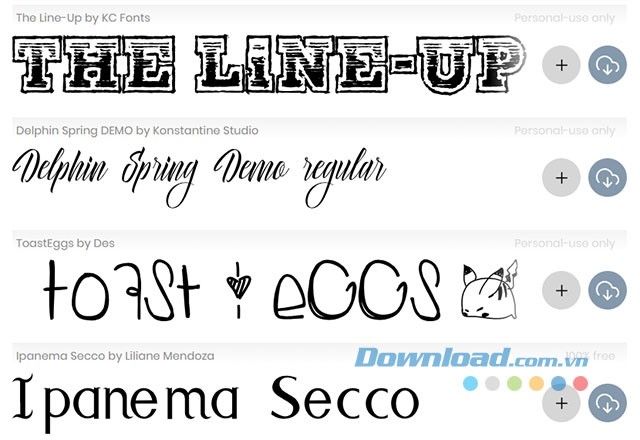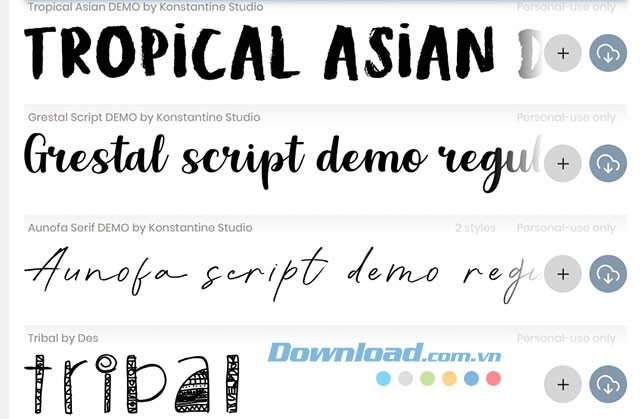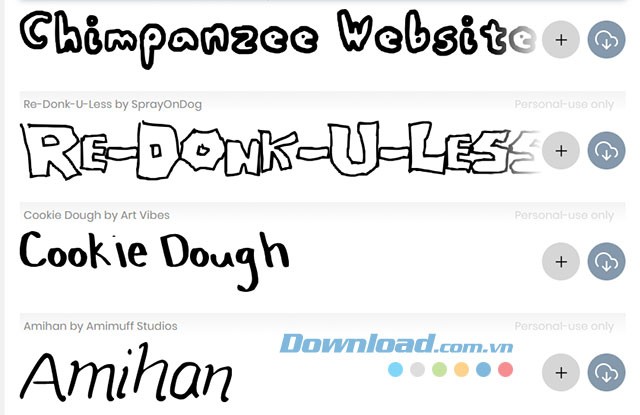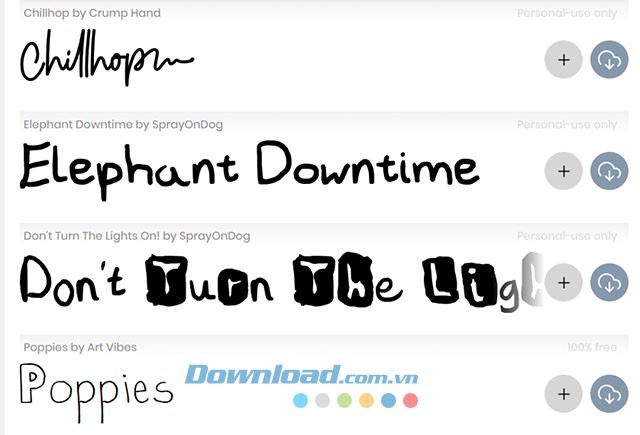
Font Chill: Bộ Font Chữ Đẹp Tiếng Anh Đầy Cảm Hứng
Font Chill là một bộ font chữ đẹp tiếng Anh, sở hữu rất nhiều kiểu chữ độc đáo và ấn tượng.
Bộ font chữ này hứa hẹn sẽ mang đến nguồn cảm hứng mới mẻ cho công việc, khơi gợi cảm giác tươi tắn, sảng khoái và niềm vui cho người sử dụng. Hãy tải và cài đặt ngay cho máy tính của bạn để bắt đầu quá trình sáng tạo những thiết kế thời thượng.
Chill – Xu Hướng Của Giới Trẻ
Sau thành công của ca khúc "Bài này Chill phết " do Đen Vâu và Min hợp tác, khái niệm "Chill" đã trở nên quen thuộc với giới trẻ Việt Nam.
Vậy, "Chill" thực sự có ý nghĩa là gì? Tại sao từ này lại được yêu thích đến vậy? Theo nghĩa đen tiếng Anh, "Chill" liên quan đến cảm giác lạnh lẽo, giá lạnh, hoặc ớn lạnh. Ví dụ, câu "There was a chill in the air" có nghĩa là "Không khí lạnh lẽo quá."
Tuy nhiên, cách mà giới trẻ Việt Nam sử dụng từ "Chill" lại mang một ý nghĩa hoàn toàn khác. Nó được hiểu như một từ lóng, tương đương với "Cool", "đẹp", "hay", "thú vị" hoặc "sảng khoái".
Nhìn chung, "Chill" mang ý nghĩa tích cực, do đó bộ Font Chill chắc chắn sẽ truyền cảm hứng sáng tạo đặc biệt, đặc biệt đối với giới trẻ.
Font Chill – Sự Lựa Chọn Mới Lạ
Bộ Font Chill là một tuyển tập gồm 21 font chữ đẹp, được thiết kế dành cho Word , mang phong cách "Chill" đặc trưng.
Đây không phải là những font chữ cứng nhắc như trong các bộ Font Vni , Bộ font TCVN3 hay Bộ font Unicode thông thường. Thay vào đó, bạn sẽ có những lựa chọn mới mẻ, mềm mại và độc đáo, chắc chắn sẽ làm hài lòng mọi người.
Bạn hoàn toàn có thể sử dụng Bộ Font Chill làm font chữ cho Photoshop để thiết kế poster, một sự kết hợp vô cùng lý tưởng.
Nguồn Cảm Hứng Sáng Tạo
Với những người làm trong lĩnh vực thiết kế đồ họa và chỉnh sửa ảnh, bộ Font Chill sẽ là nguồn năng lượng mới, kích thích sự sáng tạo và thử nghiệm để tạo ra những sản phẩm độc đáo, nổi bật và mang đậm dấu ấn cá nhân.